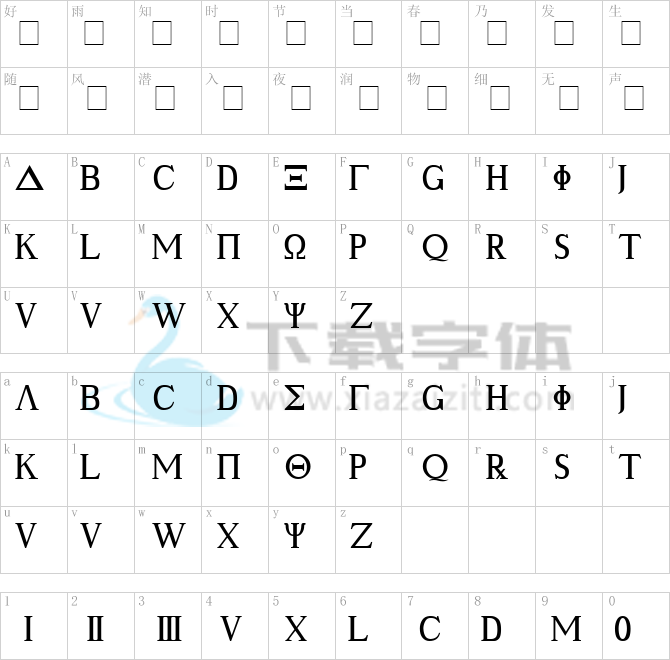
Ancient Geek.ttf字体下载,这款字体结构工整、笔画清晰,兼顾美观与易读性,适用于标题、正文、海报、包装、LOGO 等多种场景。字形优雅稳定,风格百搭耐看,适配日常排版与创意设计,让文字呈现更舒适、更具质感。Ancient Geek.ttf字体下载一笔一画,皆是细节,以均衡的比例、流畅的线条打造舒适视觉体验,字形端正大气,风格简约现代。无论是商业设计、品牌宣传还是日常排版,都能轻松驾驭,让文字更有格调与力量。Ancient Geek.ttf字体下载字体下载。